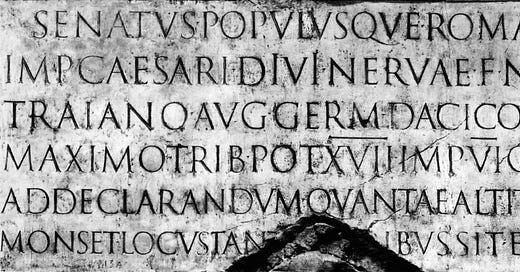
Tipo Aquilo #36 – Som e pausa, letra e espaço
Em 2002, o Winamp, famoso player de música digital para Windows, ganhou sua terceira versão. Na teoria, ele não mudava muita coisa em relação ao anterior; na prática, ele era muito menos estável, com menos recursos e um notório beberrão de memória RAM. No ano seguinte, seu sucessor, o Winamp 5 (foi 5 mesmo, eu não errei a conta) chegou ao mercado com vários recursos, mas nunca mais teve a fama que a versão 2 teve nos anos de ouro da Internet discada. Um exemplo desses recursos é o cross-fading, em que ao final de uma faixa, o Winamp já tinha lido a faixa seguinte e começado ela sem pausa. Isso foi muito maneiro, mas a falta de respiro na experiência de ouvir música com cross-fading encheu o saco 20 minutos depois.
Tipografia e música são dois grandes interesses da minha vida que são iguais em uma coisa: o funcionamento básico deles depende de como a gente alterna entre som e pausa, ou positivo e negativo. A gente dá o nome de “ritmo” a essa alternância que a gente não vê, mas sente quando está acontecendo na sua frente. O corpo tende a querer se mover no ritmo da sua música favorita, tal como o olho tende a não se distrair quando as letras e seus espaçamentos favorecem uma alternância gentil entre forma e contra-forma. O domínio da contra-forma é uma das qualidades que mais separa os designers de tipos iniciantes dos veteranos.
Primeiro, acho legal falar um pouco dos espaços mais óbvios, estes que você vê entre as palavras. São tão óbvios, mas na cultura europeia, surgiram apenas no séc. VII; antes, as palavras eram comumente marcadas por pontos em vários sistemas de escrita; ou simplesmente não eram marcadas e azar de quem tivesse que ler, já que não era muita gente mesmo. Na Europa, esse tipo de composição chamada scriptio continua agrada um lado meu que curte texturas uniformes, mas me desagrada profundamente ao imaginar a monotonia de um texto sem espaços. A escrita tinha o propósito de transcrever discursos de alguma pessoa de influência, como um filósofo ou um clérigo, para que esse discurso fosse falado enquanto lido; por isso, o scriptio continua fazia sentido.
Paul Saenger em “Space Between Words: The Origins of Silent Reading” conta que, no séc. VII, escribas irlandeses introduziram o conceito de Suflair “texto aerado”, em que espaços eram colocados ao longo do texto, mas não necessariamente entre todas as palavras. Essa presença de espaços dentro do texto é vista por alguns estudiosos como uma forma degenerada do cola et commata, uma forma de escrita em que o texto era separado por linhas que constituem ideias únicas. Apenas a partir do séc. XI que a separação de palavras por espaços tornou-se canônica, à medida em que os textos deixavam de ser meras transcrições de pensamentos.
Atualmente, não conseguimos pensar em textos sem espaços. Uma vez que a separação de palavras tornou-se comum, os espaços tornaram mais fácil rastrear e apreender informação; junto com os sinais de pontuação, eles dividem o texto em unidades de som e significado mais compreensíveis. Dessa forma, a leitura em voz alta do texto não era mais necessária para seu entendimento. A dispersão da tipografia pelo mundo a partir do séc. XV aumentou a oferta de textos escritos, tornando possível que mais pessoas tivessem cópias próprias até de volumes inteiros. Com isso, o ato de ler tornou-se predominantemente uma atividade individual, silenciosa, e em várias vezes, orientada à busca de informações, ao invés da compreensão de todo o fluxo de pensamento do texto.
O desenvolvimento da tipografia levou à criação de vários tipos de espaços, cada um com dimensões e propósitos diferentes; em fontes com números de largura fixa, existem os figure spaces, espaços equivalente à largura desses números. Existem também os espaços finos, usados entre letras e aspas ou apóstrofos; na tipografia digital, existem os espaços invisíveis e os non-breaking spaces, que separam palavras visualmente, mas impedem quebras de linha entre elas; e existem também os espaços duplos em fim de frase, costume entre usuários de máquinas de escrever que, enfim, o Word passou a mostrar como um erro de estilo.
Agora, vamos falar dos espaços entre letras (espaçamentos) e dentro das letras (contra-formas). Estes existem desde que a primeira letra foi escrita, e esses são os que mais dão dor-de-cabeça a calígrafos e designers de tipos. Inclusive, é um consenso entre type designers que espaçamentos sejam pensados ao mesmo tempo que as letras em si, pois constituem o ritmo da fonte junto com as formas e contra-formas. Fred Smeijers, em “Contrapunção: fabricando tipos no século dezesseis, projetando tipos hoje” chama de “um jogo de preto e branco” a forma com que uma mudança no espaço branco da letra provoca a alteração no espaço preto, e como ambos, no fim das contas, são uma coisa só.
Smeijers aborda também os métodos que existiam para a criação de punções. A criação de tipos móveis sempre dependeu de punções para que cada nova caixa de tipos fosse fiel ao projeto original. Era consenso que as formas externas das punções fossem cortadas e limadas, mas a criação das contra-formas dividia-se entre os gravadores que escavavam manualmente esses espaços nas punções, e os que utilizavam punções específicas para este fim. Estas eram chamadas de contra contrapunções porque eram marteladas contra outras punções que, estas sim, eram usadas para criar tipos móveis.
(explicar tudo isso é complicado, por isso aconselho ver o vídeo recomendado no final dessa edição)
As punções tinham dimensões práticas e simbólicas para o gravador; punções podiam ser herdadas e transferidas por gerações de gravadores, como um atestado de qualidade das fontes que ajudaram a criar. Em termos práticos, o uso de contrapunções para os espaços negativos das letras é mais do que um acréscimo de eficiência na criação de tipos; em várias fontes, as letras “p”, “b”, “d” e “q” têm contraformas iguais, variando apenas a posição. Com isso, usava-se uma única contrapunção para quatro letras, enquanto a escavação exigia quatro procedimentos manuais pra cada letra. Isso representa um pensamento de design na criação de tipos, de forma que as ferramentas são reflexo de um sistema visual conciso com pequenas variações, essencial para a produção em série de tipos.
Falar do espaço em branco na tipografia também envolve falar do espaçamento entre as letras. No ensino de tipografia, uma analogia que ajuda a entender esse equilíbrio entre espaços internos e externos é pensar esses espaços como reservatórios de água. Numa composição tipográfica ideal, os espaços entre as letras devem comportar o mesmo volume de água, e os espaços dentro das letras também devem comportar esse mesmo volume de água. Esse balanço muda um pouco, de acordo com cada fonte e seu devido propósito, mas é algo que passa longe de ser determinado por valores absolutos. Às vezes é necessário criar kernings, que são espaçamentos entre pares específicos de letras. Mesmo na tipografia digital, que conta com o poder dos computadores para fazer cálculos precisos, esse equilíbrio é alcançado apenas com a mais poderosa das ferramentas: o olho humano.
Recomendações:
🎧 Podcast: Janacast, com Janaína Branco, Jota Vilanova e Sara Régia discutindo sobre tipografia e seu ensino no Laboratório de Tipografia do Agreste (LTA-UFPE).